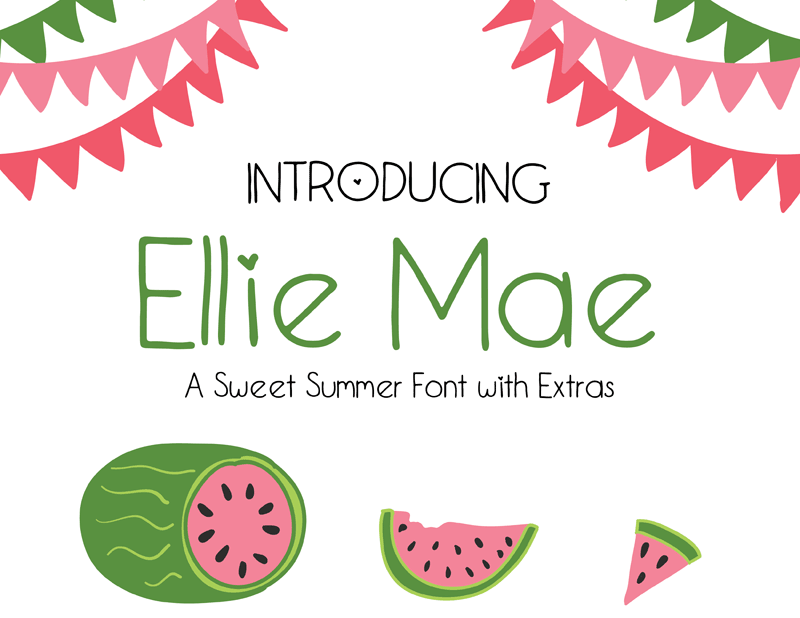
Ellie Mae Font
A Ellie Mae Font é uma fonte à mão livre criada por Hamilton, perfeita para aqueles que desejam adicionar um toque autêntico e delicado a seus projetos digitais. Com um design elegante e fluido que se assemelha às escritas manuscritas de profissionais, esta fonte inclui letras maiúsculas e minúsculas, números e símbolos. Além disso, oferece uma coleção adicional de ilustrações clip-art, permitindo ao usuário experimentar diferentes maneiras de incorporar a Ellie Mae em suas criações digitais. Combinada com um design naturalista que evoca memórias da escrita de papéis manuscritos antigas e dos anos 80, esta fonte é uma excelente escolha para designers apaixonados por criar ambientes sutis e acolhedores, seja em aplicativos de mensagem pessoais ou em designs de web responsivos. Ela se destaca como uma fonte de escrita à mão livre perfeita para projetos que valorizam a sofisticação elegante combinada com um toque autêntico e personalizado. Visite o site da Millie Mae and Co. para obter mais detalhes sobre esta incrível fonte, incluindo as opções de compra para o seu projeto.